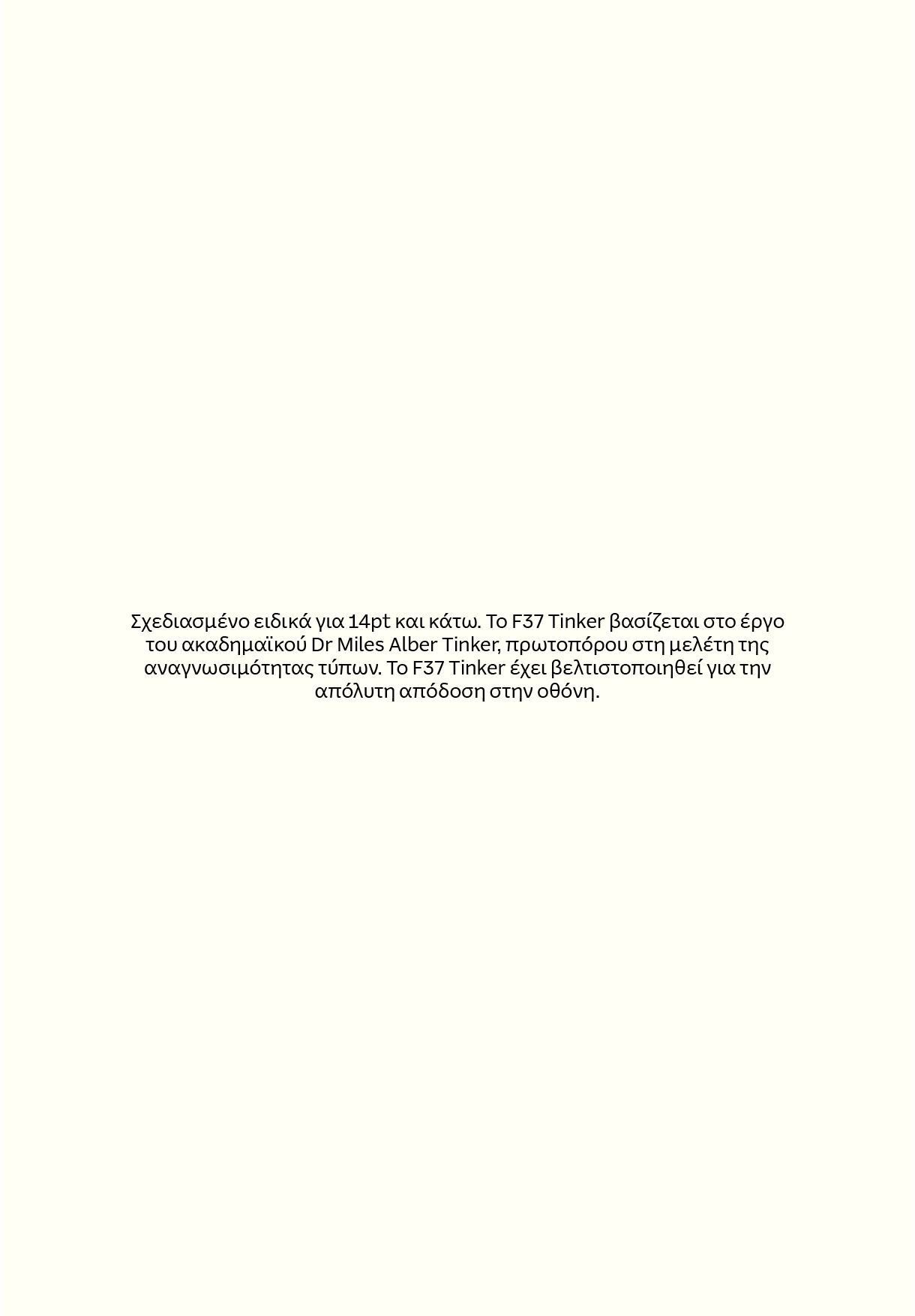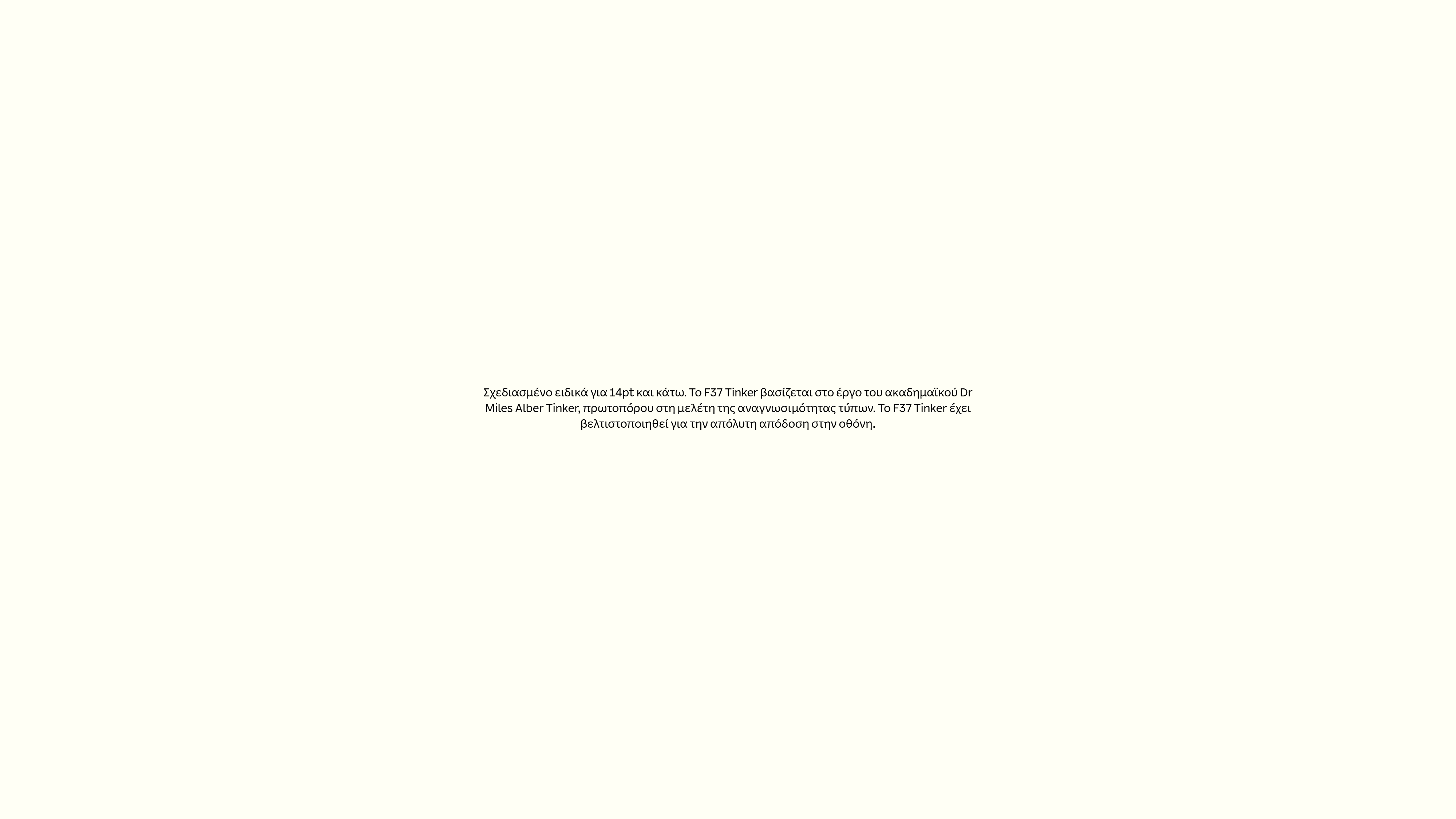
F37 Tinker Greek Font Sampler
Το F37 Tinker είναι ο φόρος τιμής μας στον επιδραστικό Αμερικανό συγγραφέα και επιστήμονα Dr. Miles Albert Tinker, πρωτοπόρο στη μελέτη της αναγνωσιμότητας τύπων.